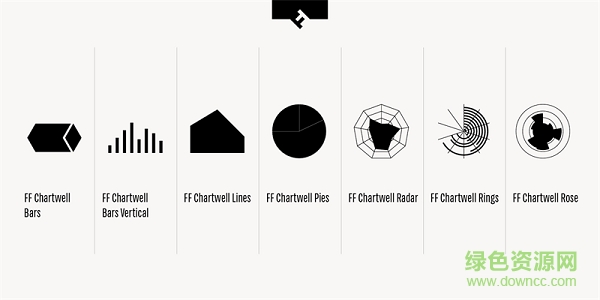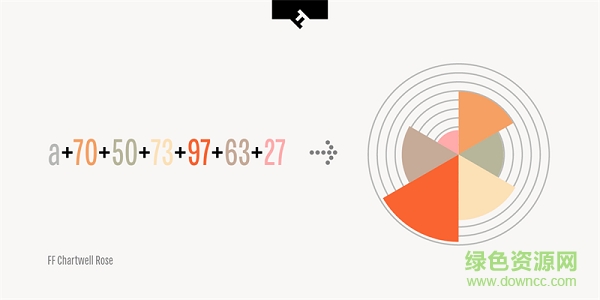
ff chartwell font family
ff chartwell font family包含了多款漂亮的信息圖表字體,用戶只需輸入數(shù)字即可轉(zhuǎn)變?yōu)楦魇綀D表,時尚精美,操作簡單便捷,有需要的朋友快來下載吧!
ff chartwell字體介紹
這是一套專門用來做數(shù)據(jù)可視化的字體,支持windows和mac,如黑科技一般,只要使用了這套字體,就能馬上得到漂亮的圖表。這套字體包含七種字體,分別可以做柱狀圖、餅狀圖、雷達圖、玫瑰圖等7類圖表。